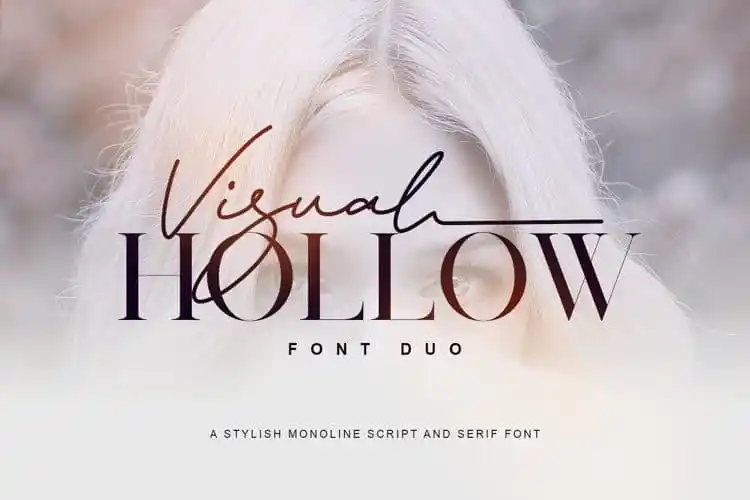
Visual Hollow Font Duo
Introduzimos Visual Hollow Font Duo, uma combinação única que une a elegância dos traços serifados com o charme das tipografias script. Este conjunto de duas fontes é ideal para quem busca criar algo único e original, misturando elementos de diferentes estilos. Cada versão (serif e script) traz sua própria identidade visual, permitindo que você utilize as duas juntas ou em separado. Desenvolvida por um criativo designer chamado Lemonthe, a Visual Hollow Font Duo oferece uma grande liberdade para explorar suas possibilidades. Com sua disposição de letras precisa e sofisticada, essa fonte é perfeita para trabalhos que exigem tanto elegância quanto criatividade, como capas de livros, identidades corporativas ou design gráfico. Com Visual Hollow Font Duo, você pode se aventurar e transformar seus projetos em verdadeiros estandartes, adicionando um toque diferenciado que distinguirá suas criações das demais. Experimente essa combinação única para trazer vida à sua próxima obra de arte visual.